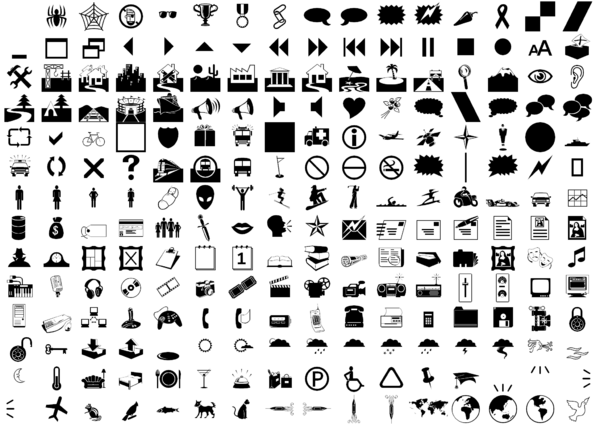
Нестандартные шрифты
Нестанда́ртные шрифты́ — компьютерные шрифты, расположение глифов в которых не соответствует общепринятым кодировкам. Такие шрифты могут включать в себя:
- знаки экзотических систем письма;
- технические символы;
- пиктограммы;
- декоративные символы.
Распространение нестандартных шрифтов началось одновременно с появлением в текстовых процессорах возможности переключения шрифтов — это позволяло неограниченно наращивать набор используемых знаков, не выходя при этом за рамки технологии 8-битных символов.
Нестандартные шрифты широко используются и при локализации игр: часто в играх применяется собственный шрифтовой движок, и, чтобы удовлетворить его ограничения, иногда приходится исправлять кодировку. Изредка приходится вмещать в 8-битную кодировку сразу несколько алфавитов (например, имена поворотов в автосимуляторах — см. схему автодрома Интерлагос).
В то же время использование нестандартных шрифтов влечёт и очевидные неудобства: при отсутствии доступа к конкретному шрифту невозможно определить, какой символ должен изображаться, поэтому при переносе документа на другой компьютер все нестандартные символы могут превратиться в кракозябры (то же самое происходит про просмотре веб-страниц на компьютере, где отсутствует определённый нестандартный шрифт).
Юникод и нестандартные шрифты
Внедрение Юникода уменьшило потребность в нестандартных шрифтах, поскольку все широко используемые символы получили свои кодовые позиции. В Юникоде предусмотрена и возможность использования «пользовательских символов» — для них отведены отдельные области U+E000—U+F8FF и U+FFF80—U+10FFFF.
Наряду с этим существуют и такие шрифты, в которых нестандартные символы размещены «нелегально» — на позициях, отведённых для других символов. Особенно популярно размещение нестандартных символов в позициях 0x20—0xFF: это делает их доступными для программ, не использующих Юникод. Например, русские шрифты TrueType раньше часто делались так, что русские буквы занимали позиции U+00C0—U+00FF (позиции расширенной латиницы), вместо правильных U+0410—U+044F — это позволяло, например, работать с кириллицей в ранних нерусифицированных версиях Windows.
Примеры нестандартных шрифтов
WordPerfect поставлялся с большим набором нестандартных шрифтов (например, для кириллицы, греческого алфавита и т. д.). В своё время химиками широко использовался редактор ChiWriter, который имел собственный шрифтовой движок со встроенным редактором — но в нём была только первая половина кодовой таблицы. Так что русские пользователи создавали нестандартный шрифт, соответствующий русской клавиатурной раскладке (Q → Й и т. д.)
Microsoft Windows включает несколько нестандартных шрифтов: Symbol (греческие буквы и математические символы), Wingdings (пиктограммы и декоративные символы), Webdings (пиктограммы).
Компания ПараТайп выпускала ряд нестандартных шрифтов: для русского в старой орфографии, для «азиатской кириллицы», для грузинского, армянского, древнегреческого и т. д.[1]